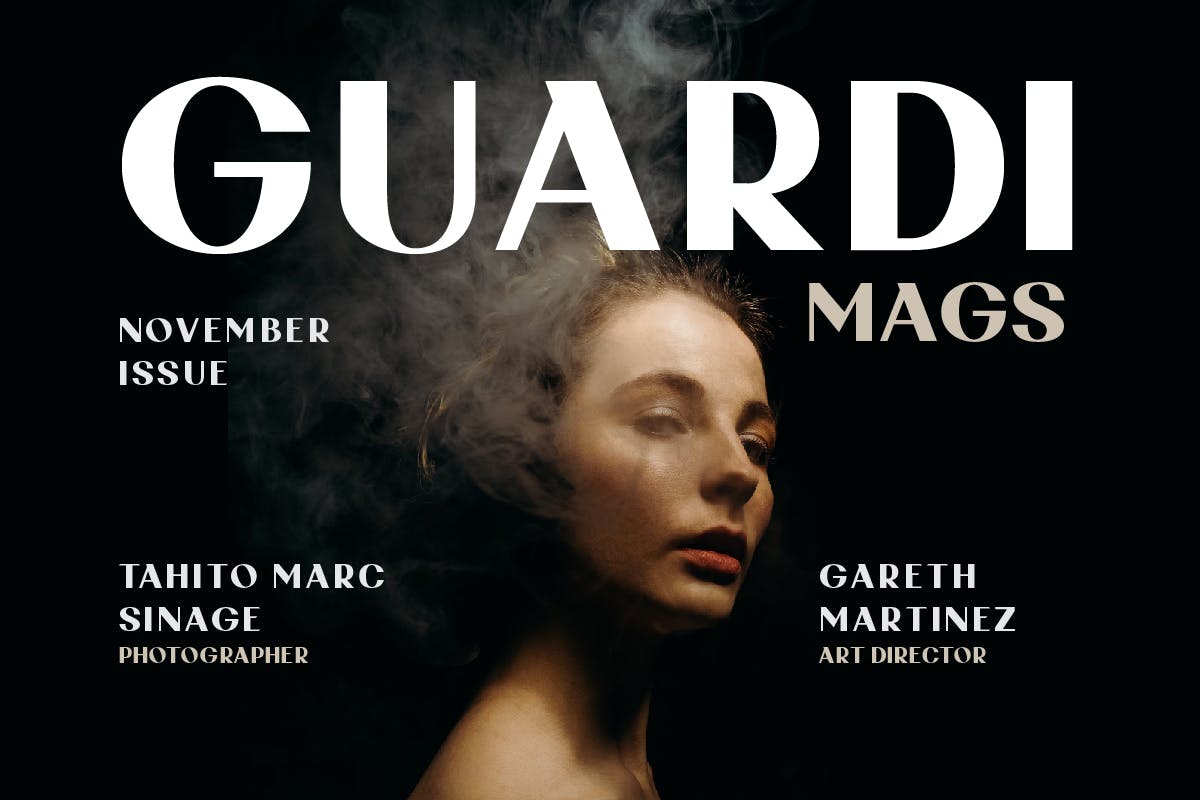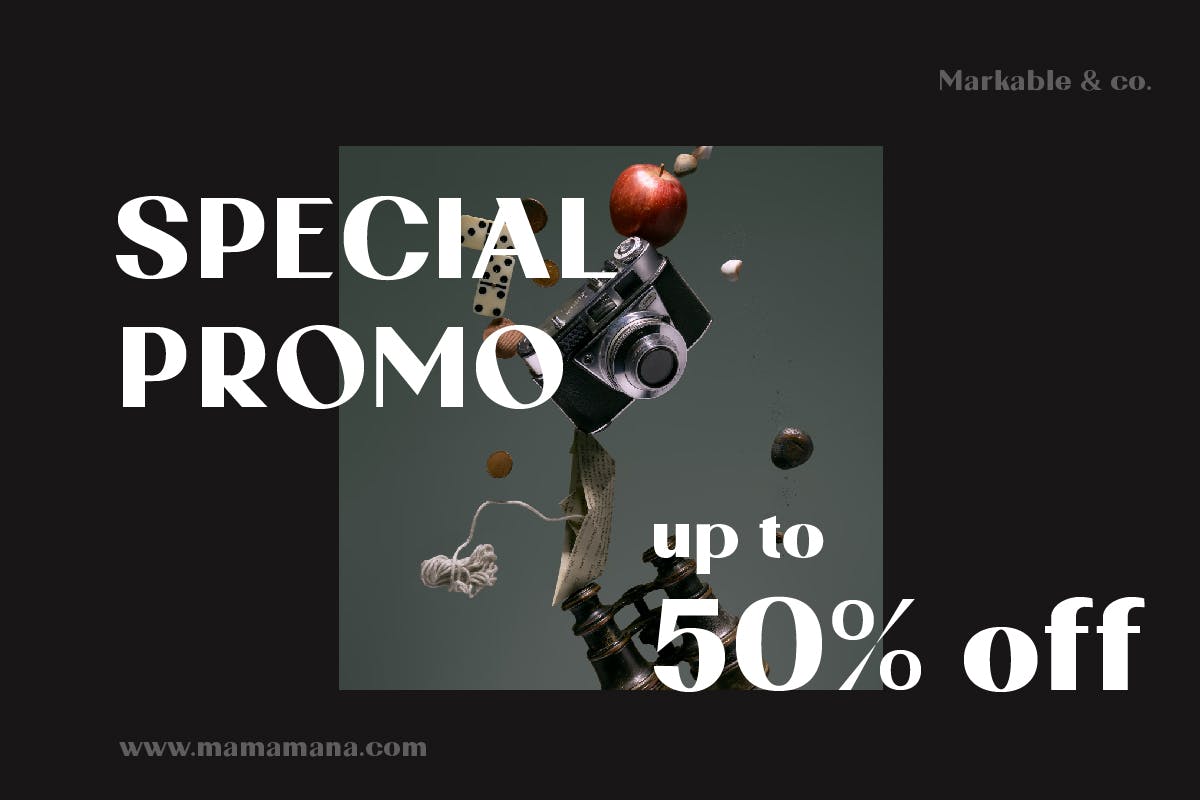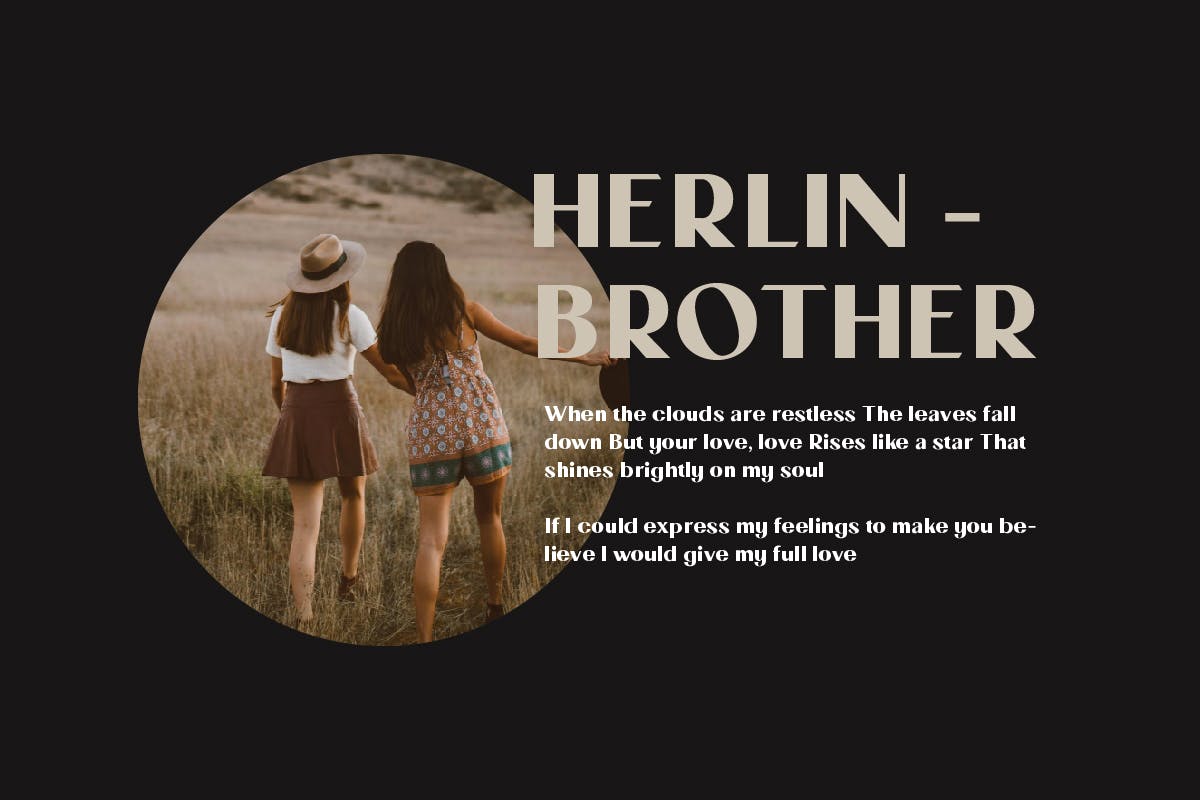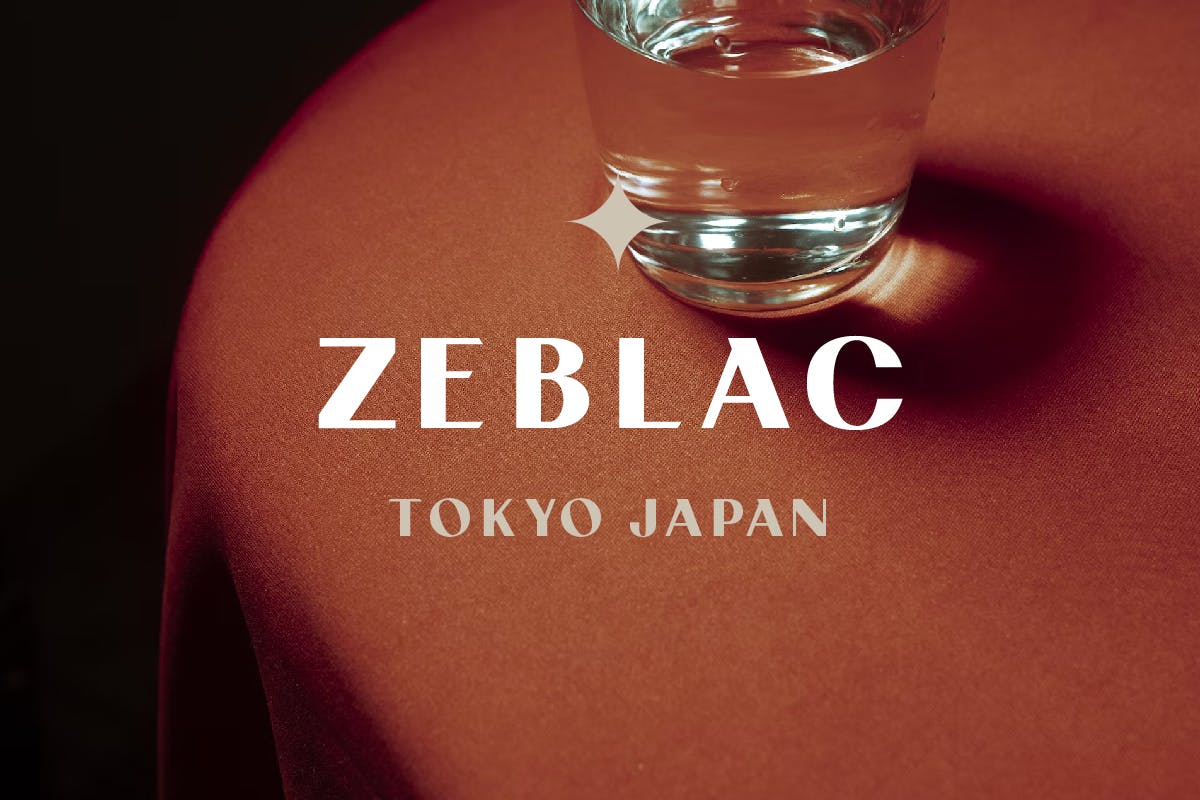
آیا شما یک هنرمند یا فرد خلاق هستید که میخواهید خود را متمایز کنید؟ فونت دسمن مدرن سانس، یک فونت منحصر به فرد و مد روز را به شما معرفی میکند.
این فونت برای برندینگ مد لوکس، ویدیوهای سینمایی، عناوین شبکههای اجتماعی و سایر آثار خلاقانه عالی است! چه چیزی این فونت را از بقیه متمایز میکند؟ خوانایی آسان و در عین حال ظرافت آن.
و با اینکه این فونت خود دارای جذابیت است، نیازی به افزودن چیز دیگری نیست. فقط کافی است فونتها را در اندازهها و چیدمانهای مختلف استفاده کنید—و شما یک اثر هنری واقعاً خیرهکننده میسازید!